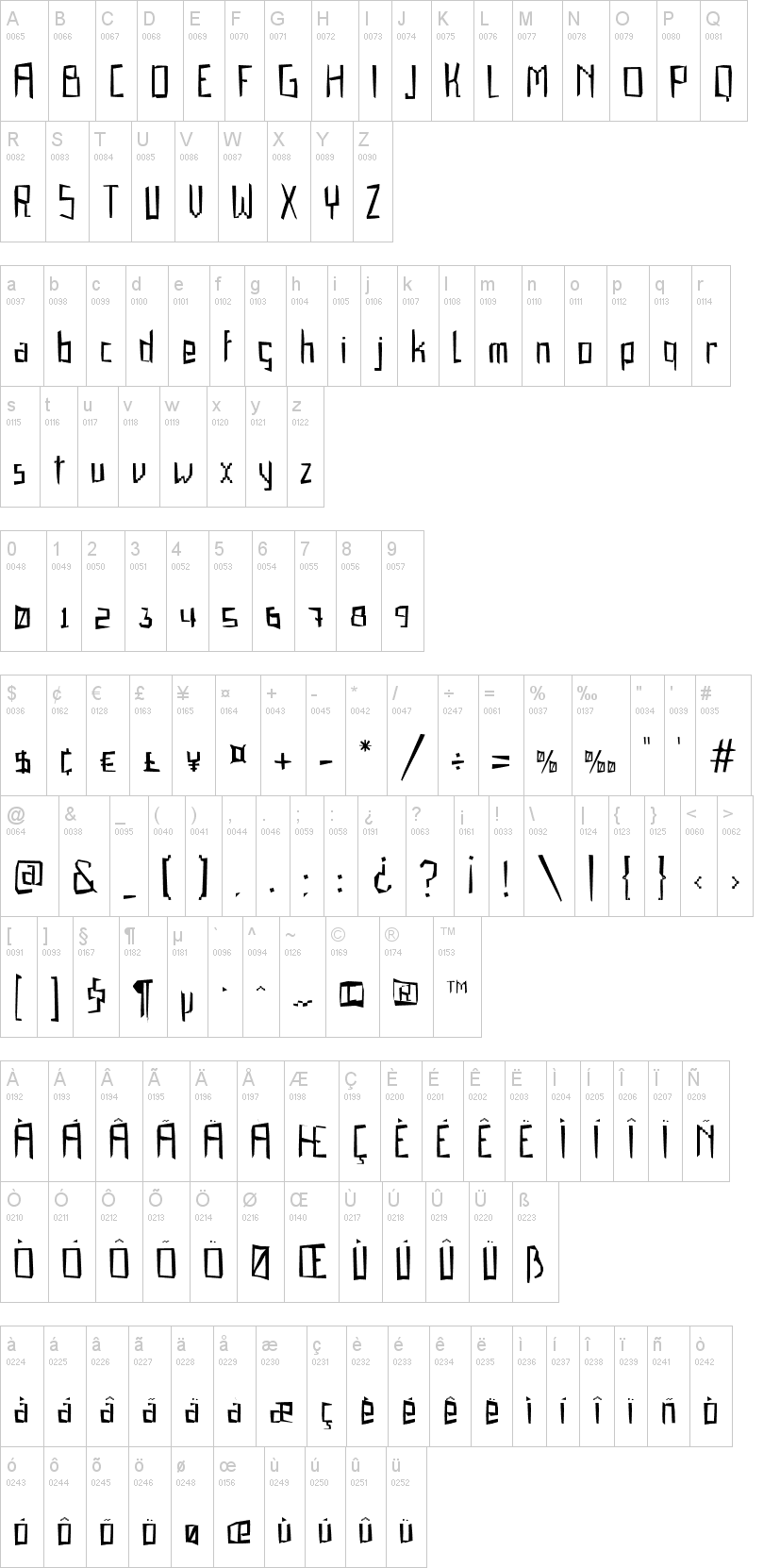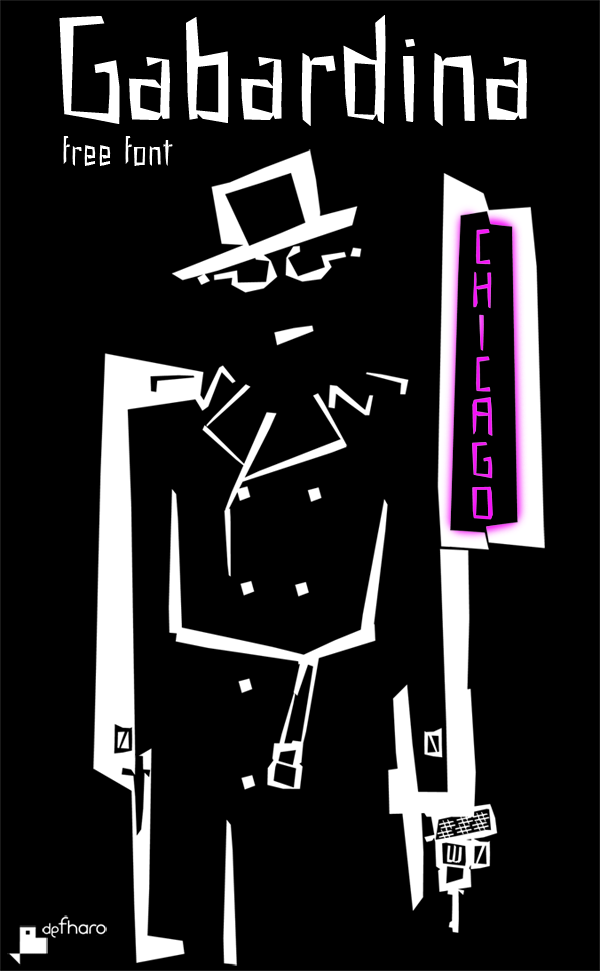
Шрифт Gabardina
Gabardina es una font distorsionada de lineas rectas que puedes usar en carteles, posters y logotipos. Tiene funciones OpenType con números y ligaduras. Comment please